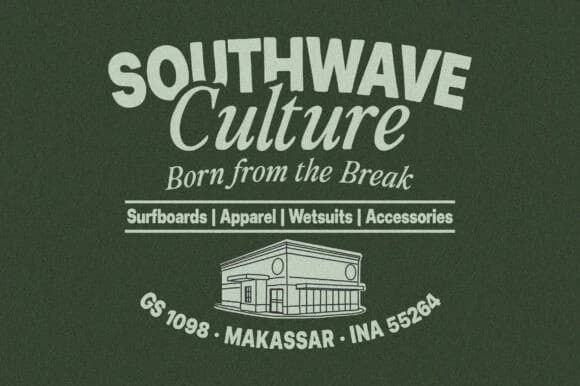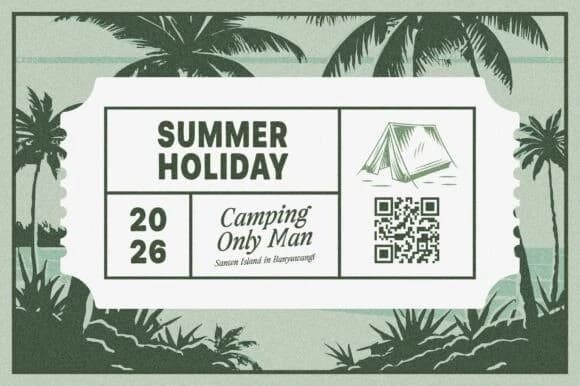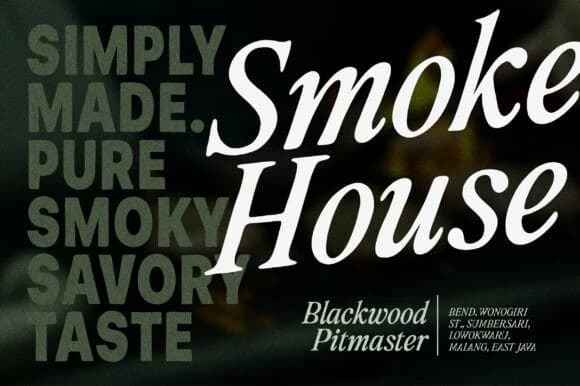
Eloura Blend Font, zarif bir serif ile temiz, sade bir sans serif'i bir araya getiren modern bir font ikilisidir. Bu ikili, doğal ve okunması kolay bir his vermesi için tasarlandı; aynı zamanda güçlü ve ayırt edici bir karakter taşıyor.
Eloura Blend Font, zarif bir serif ile temiz, sade bir sans serif'i bir araya getiren modern bir yazı tipi ikilisidir. Bu ikili, doğal bir his vermesi ve kolay okunabilir olması için tasarlanmıştır ve aynı zamanda güçlü ve ayırt edici bir karakter taşır.